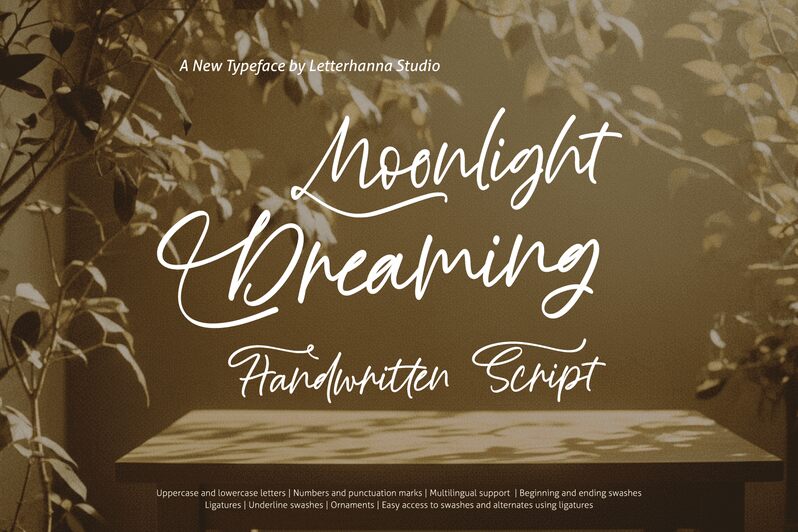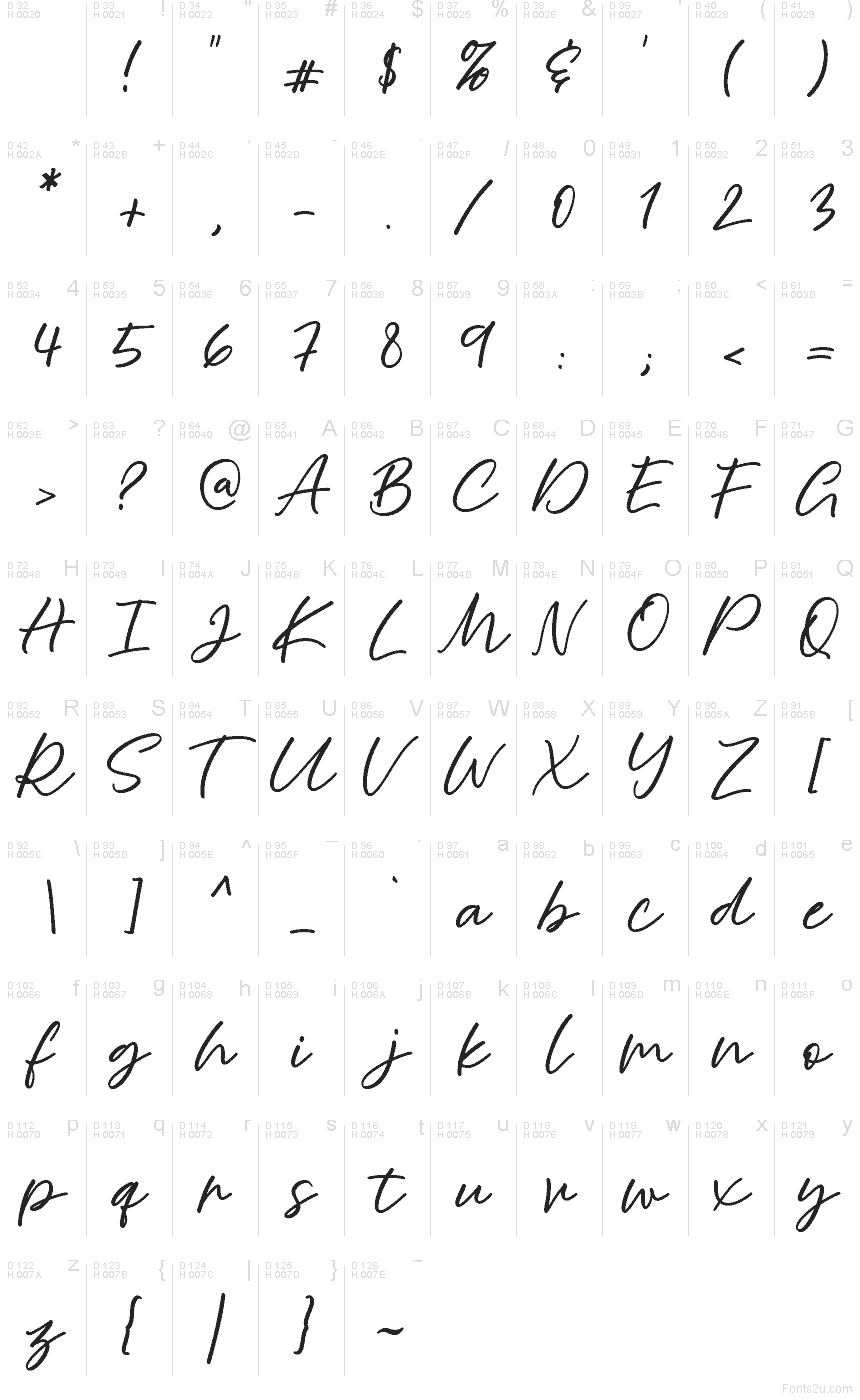
Moonlight Dreaming, créée par Rinaldo Hasibuan du studio Letterhanna, est une police manuscrite gratuite au tracé fluide et aérien, comme un reflet de clair de lune. Ses lettres se distinguent par de longues ascendantes et des boucles arrondies, conférant à la typographie un rythme onirique, à la fois léger et naturel.
Elle est idéale pour l'identité visuelle de boutiques, le packaging de produits de beauté, les menus de cafés, les cartes de vœux ou les posts sur les réseaux sociaux, là où une touche douce et personnelle prime sur la formalité. En tant que police gratuite, elle fonctionne également très bien pour les titres, les citations courtes ou les textes d'accroche, car ses larges extensions en début et fin de mot apportent du mouvement même aux textes les plus courts.